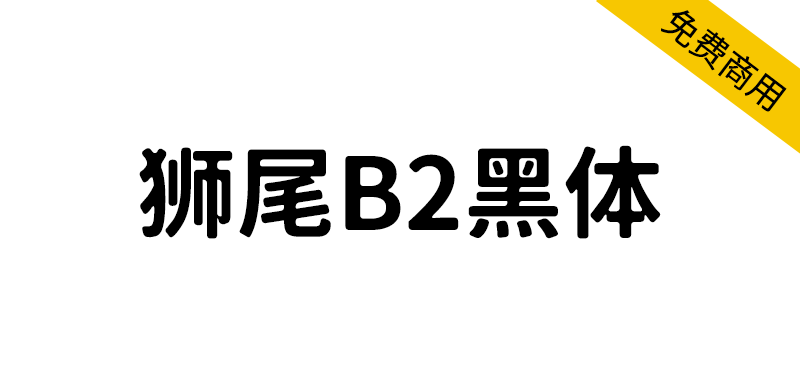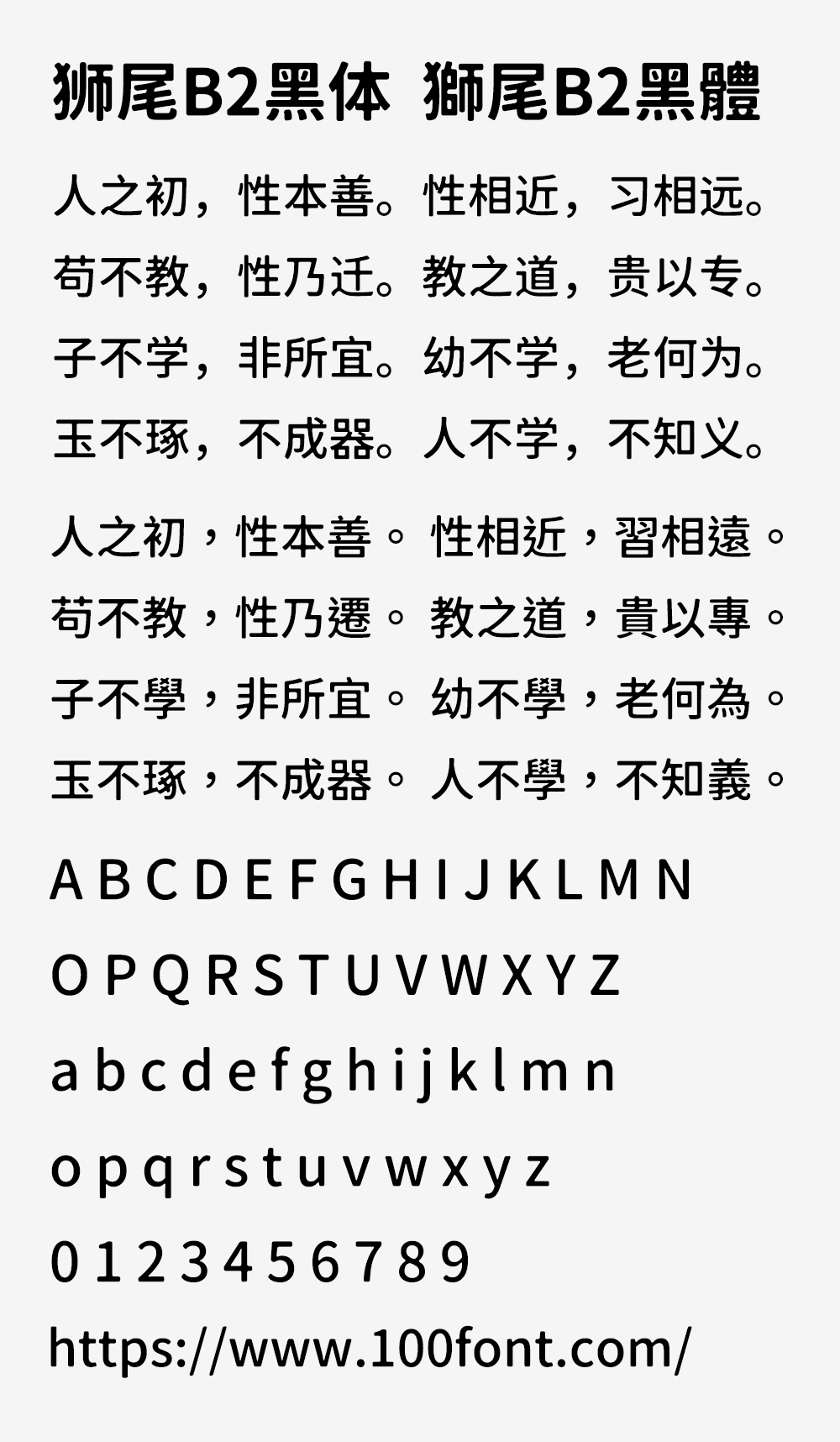
狮尾B2黑体基于思源黑体的转角的三角形转成半圆形改造,仿佛墨晕或是稍微过曝的效果。和思源黑体一样,有7种字重,支持简体中文、繁体中文、韩文与日文,可以免费商用,欢迎大家自由应用、自由优化、自由改作!
狮尾B2黑体和「狮尾B2腿黑体」差别有有没有拔脚。 「有拔脚」的字会较圆,但是会造成有些字因直接去掉腿后左右不平衡、左右不对衬的「悬空」问题。使用「腿」系列就比较不会有问题。